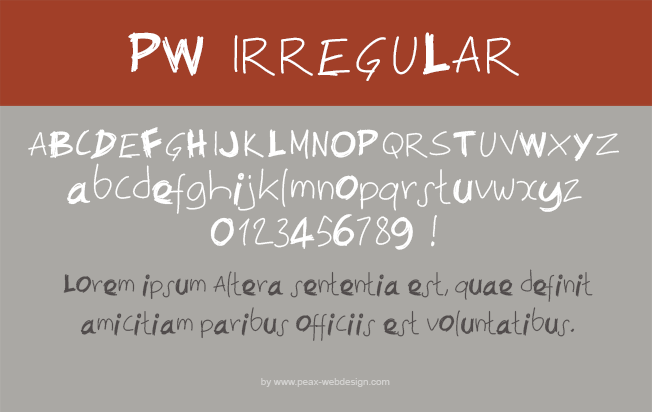
PW Irregular, police manuscrite .ttf
Vous recherchez une typo originale ? Essayez PW Irregular ! Cette police de caractères manuscrite a la particularité de présenter une différence de style sur certaines lettres, qui sont sur-épaissies. Cela crée un effet dynamique et spontané assez efficace. L'essayer c'est l'adopter !